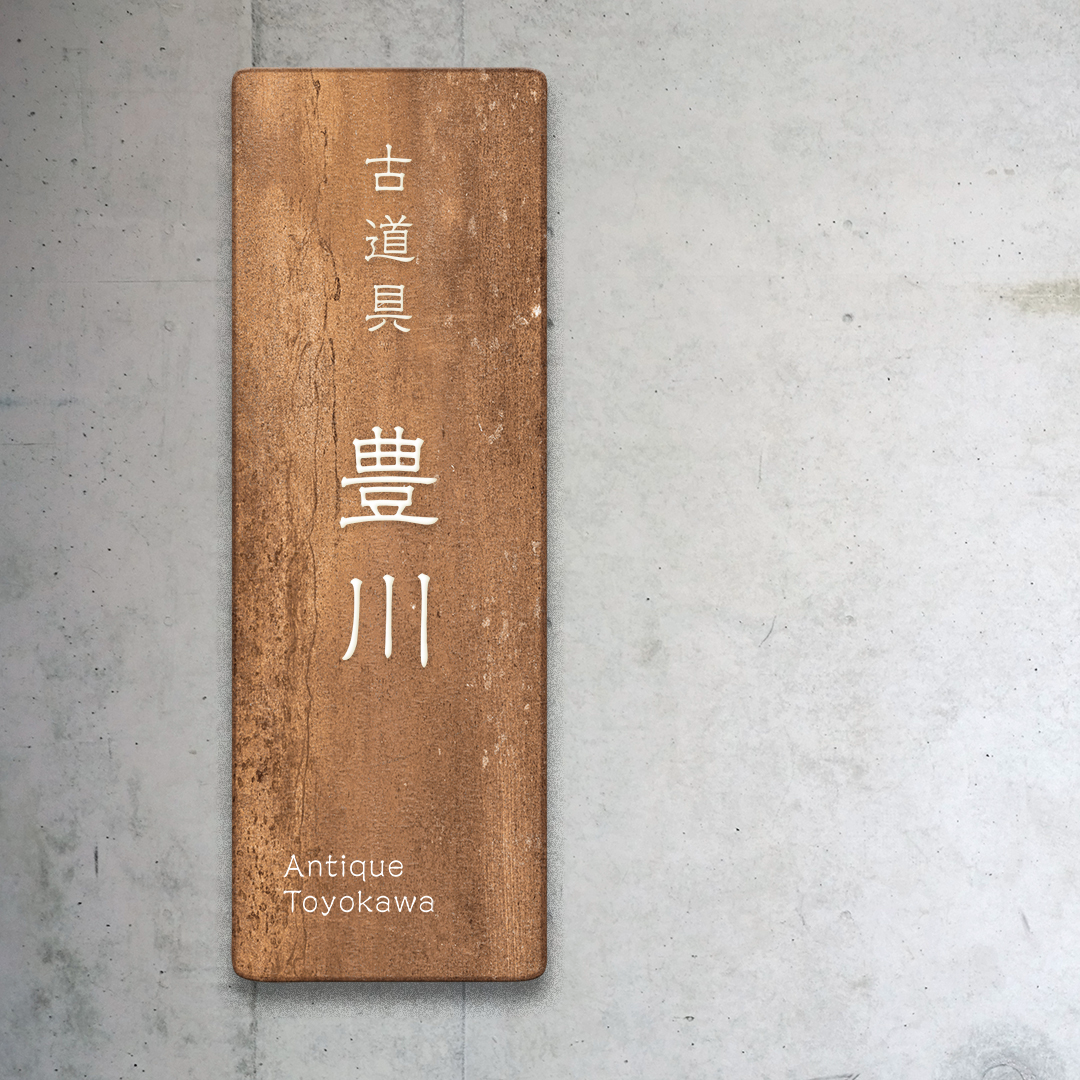
「隷書E1」について
モリサワの歴史の中でも、最初期から親しまれている隷書体の1つが隷書E1です。デジタルフォント化の際に、より滑らかな線質で使いやすい太さのデザインへと整理されています。骨格が正方形をベースとしており、それぞれの文字が大きめに設計されているため、印章などの用途にも広く用いられてきたフォントです。
「隷書E1」の特徴
隷書E1のデザインでは、隷書ならではの角ばった見え方とともに、繊細な筆の動きも表現されています。そのため、ややクセのある印象を与えたい場合には特に便利です。古さと新しさが両立されているような独特なフォントと言えるでしょう。
印章に使いやすいことはもちろん、ひらがなに流れがあって読みやすいため、見出しなどにも活用できるフォントです。ややミステリアスな雰囲気も演出しやすく、古美術や宝石に関するデザインでも重宝されます。
隷書E1は、上品さ、高級感、安定感、伝統、老舗感、和風の雰囲気の表現に大変有効で、個人的にも使用頻度が高いフォントです。作例では、文字を徹底して木と馴染ませました。フォントは平面的なものですが、サインとして使う場合には、ベベル加工やラウンド加工などの立体的な処理との組み合わせが効果的です。
タイトル・見出し、商品パッケージ、看板、印章
「隷書E1」の書体情報